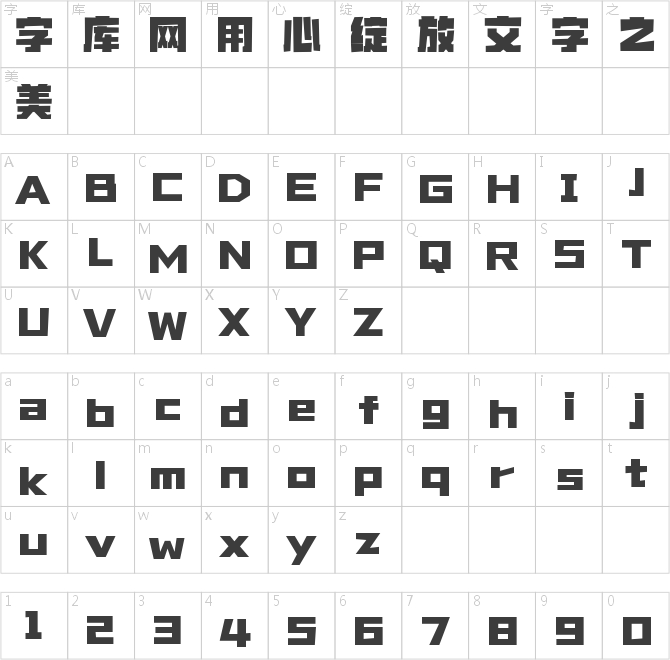
山海機甲粗黑,是一款綜藝標題黑體字體,包含簡體漢字6763個。該字體是一款具有強勁視覺沖擊力的綜藝風格標題字體。字形充實填滿整個字框,造型硬朗,全直線的筆畫構成棱角分明、堅實有力。
山海機甲粗黑字體字庫是一款讓人賞心悅目、百看不厭的中文字體,適合各類廣告和產品包裝設計應用,字體大小1.41MB,格式為ttf字體,上傳用戶是山海字庫,作者/版權方為山海字庫